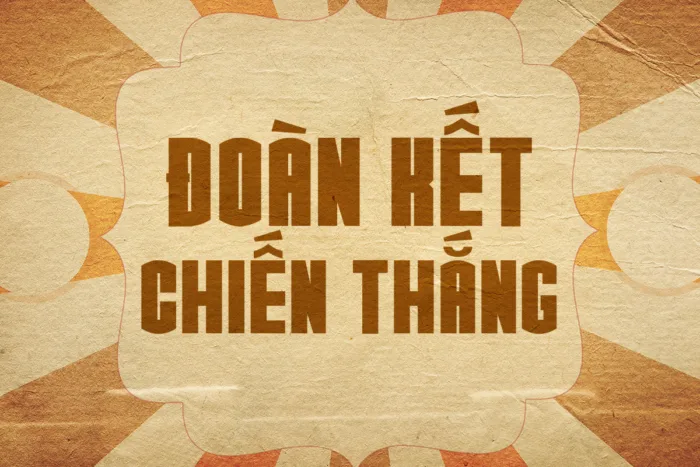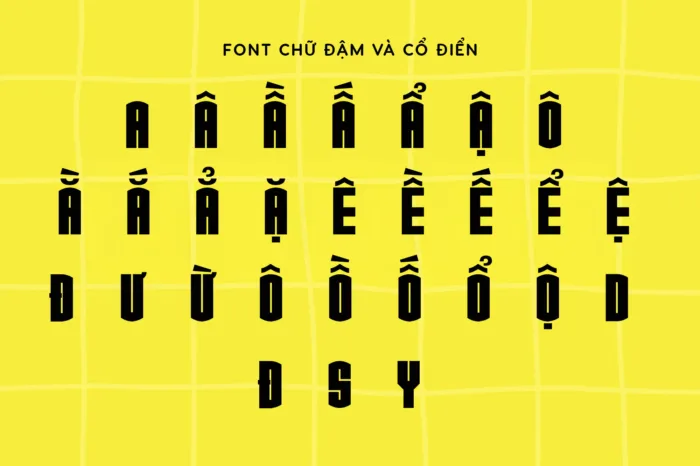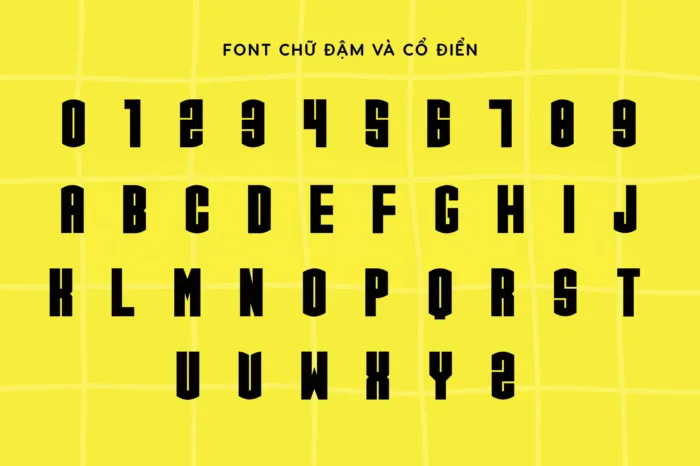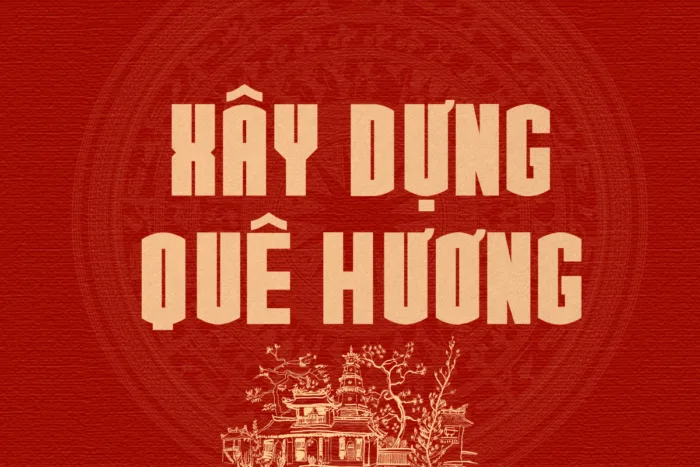
CGF Arch Reactor Việt hóa – Font chữ mạnh mẽ cho game và thiết kế fantasy
DVN – CGF Arch Reactor là font chữ Việt hóa mang phong cách đậm chất game hành động và giả tưởng, với thiết kế chữ khối mạnh mẽ, viền sắc nét và hiệu ứng kim loại – lửa đặc trưng. Font tạo cảm giác anh hùng, sức mạnh và phiêu lưu, rất phù hợp cho các dự án logo game, banner, poster phim, bìa truyện tranh, hay thiết kế tiêu đề fantasy. Phiên bản Việt hóa hỗ trợ đầy đủ dấu tiếng Việt, giúp bạn dễ dàng ứng dụng trong các dự án sáng tạo mà vẫn giữ nguyên được tinh thần mạnh mẽ của bản gốc.